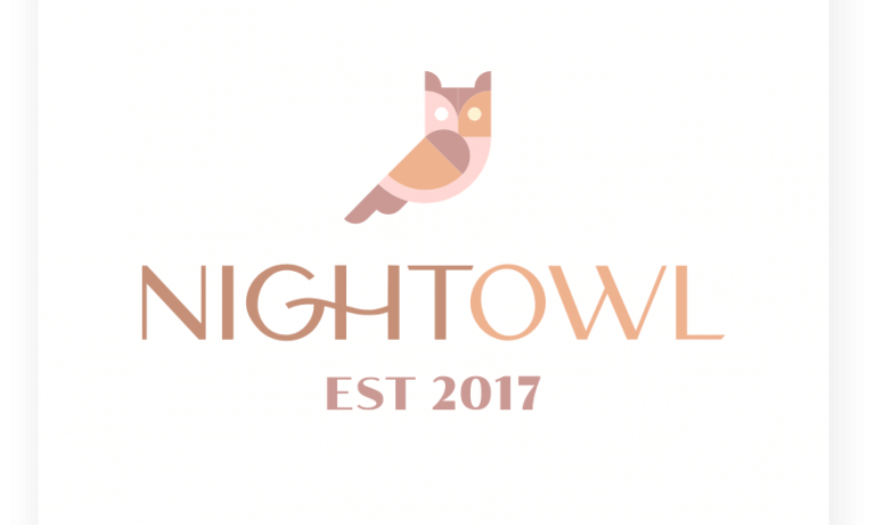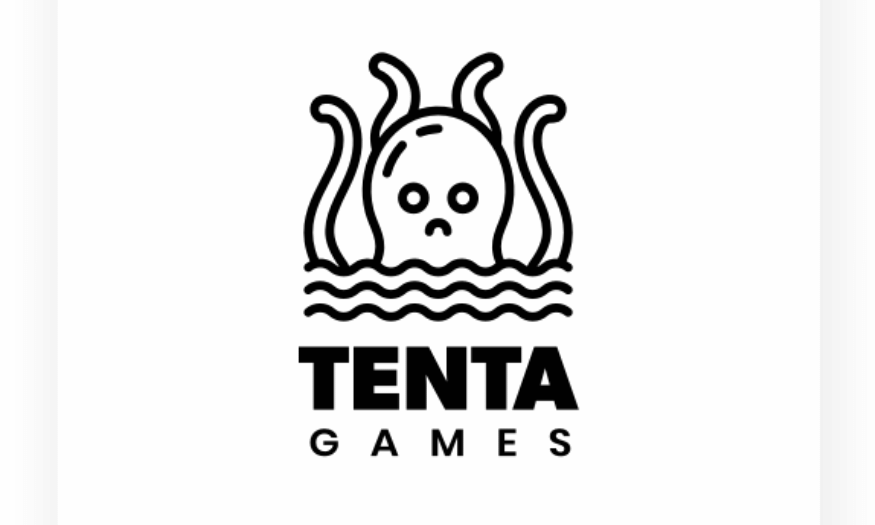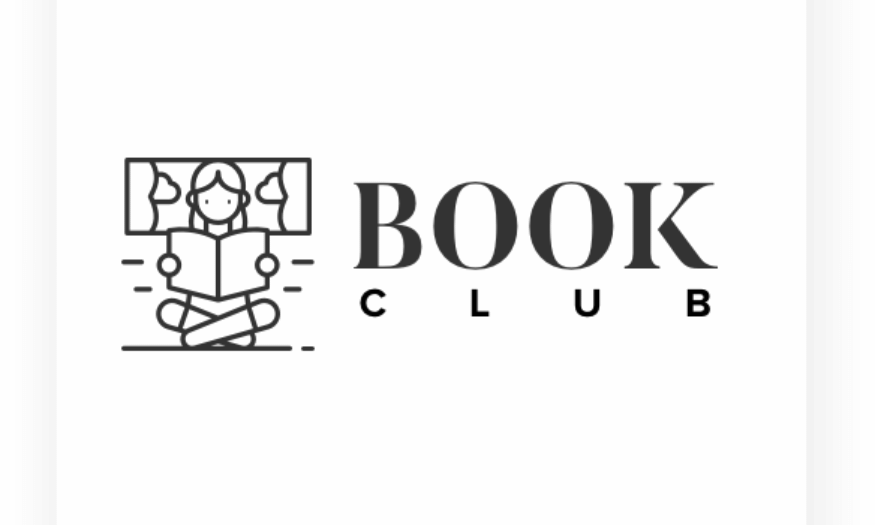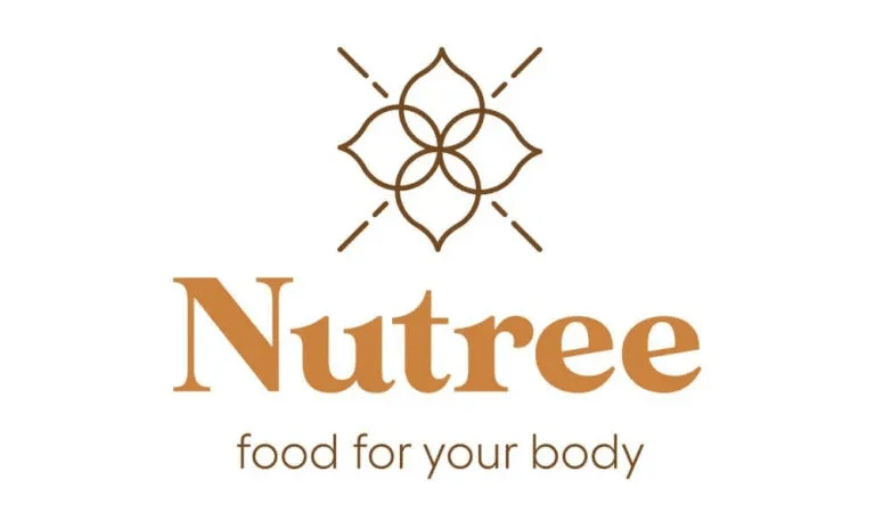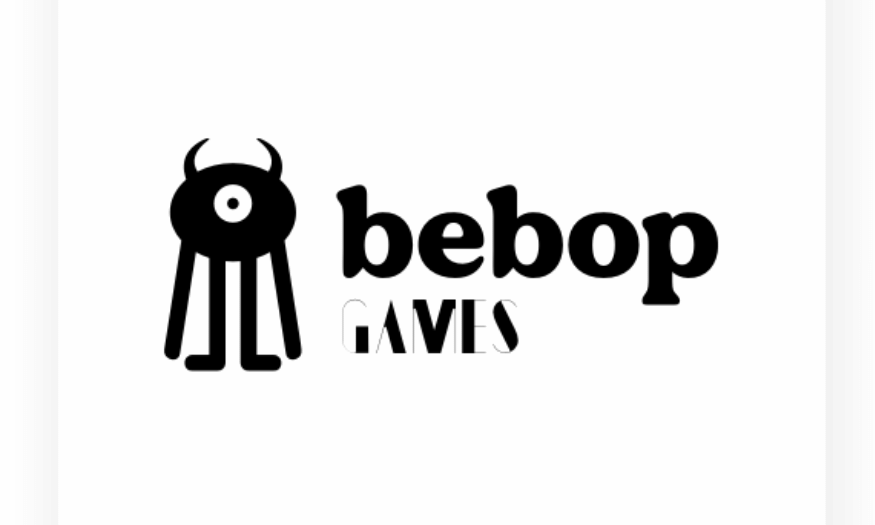
Cách Ghép Font Chữ Thiết Kế Logo Chuyên Nghiệp
Trong thế giới thiết kế logo, việc chọn và ghép font chữ là một trong những yếu tố quan trọng quyết định sự thành công của thương hiệu. Một logo không chỉ cần đẹp mắt mà còn phải truyền tải được thông điệp của doanh nghiệp một cách hiệu quả. Việc kết hợp các font chữ một cách hợp lý không chỉ giúp tạo ra sự độc đáo mà còn làm nổi bật được bản sắc thương hiệu. Trong bài viết này, Sadesign sẽ cùng bạn khám phá các bước cơ bản và những mẹo hữu ích để ghép font chữ một cách chuyên nghiệp, giúp logo của bạn trở nên nổi bật và dễ nhớ hơn.
Cách Ghép Font Chữ Thiết Kế Logo Chuyên Nghiệp
Trong thế giới thiết kế logo, việc chọn và ghép font chữ là một trong những yếu tố quan trọng quyết định sự thành công của thương hiệu. Một logo không chỉ cần đẹp mắt mà còn phải truyền tải được thông điệp của doanh nghiệp một cách hiệu quả. Việc kết hợp các font chữ một cách hợp lý không chỉ giúp tạo ra sự độc đáo mà còn làm nổi bật được bản sắc thương hiệu. Trong bài viết này, Sadesign sẽ cùng bạn khám phá các bước cơ bản và những mẹo hữu ích để ghép font chữ một cách chuyên nghiệp, giúp logo của bạn trở nên nổi bật và dễ nhớ hơn.
1. Ghép hai font chữ từ cùng một họ font
Khi bắt đầu hành trình thiết kế logo, việc lựa chọn font chữ phù hợp là một trong những quyết định quan trọng nhất. Sử dụng font chữ từ cùng một họ không chỉ giúp bạn tạo ra sự hài hòa mà còn mang lại cảm giác nhất quán cho toàn bộ thiết kế. Họ font chữ được phân loại thành nhiều nhóm như serif, sans serif, thảo mộc, và monospace, mỗi nhóm có những đặc điểm riêng, giúp bạn dễ dàng tìm kiếm những font chữ bổ sung cho nhau.
Một lợi thế lớn khi sử dụng font chữ cùng họ là bạn có thể tận dụng đa dạng các kiểu dáng mà chúng cung cấp. Ví dụ, một họ font chữ có thể bao gồm các lựa chọn về trọng lượng (độ dày hoặc độ mỏng), kích thước và cách viết hoa. Điều này cho phép bạn linh hoạt hơn trong việc thiết kế mà vẫn duy trì được sự nhất quán. Logo NIGHTOWL là một ví dụ điển hình, với sự kết hợp hoàn hảo giữa các kiểu chữ trong cùng một họ, tạo nên một cái nhìn gắn kết và dễ nhớ.
Ngoài ra, việc lựa chọn font chữ từ cùng một họ giúp bạn tiết kiệm thời gian tìm kiếm và thử nghiệm. Bạn sẽ không phải lo lắng về việc các font chữ có bị xung đột hay không, vì chúng đã được thiết kế để hòa hợp với nhau. Điều này góp phần tạo ra một trải nghiệm người dùng tốt hơn, khi người xem dễ dàng nhận diện thương hiệu và thông điệp mà bạn muốn truyền tải.
2. Font chữ dày kết hợp tốt với một font chữ mỏng
Một trong những kỹ thuật hiệu quả nhất trong thiết kế logo là tạo ra sự tương phản giữa các font chữ. Sự kết hợp giữa một font chữ dày và một font chữ mỏng không chỉ giúp nâng cao tính thẩm mỹ mà còn làm rõ ràng thông điệp mà bạn muốn truyền tải. Font chữ dày thường mang lại cảm giác mạnh mẽ, trong khi font chữ mỏng lại tạo ra sự tinh tế và nhẹ nhàng.
Khi kết hợp hai loại font chữ này, điểm chính là phải đảm bảo rằng chúng đủ tương phản để người xem có thể dễ dàng phân biệt. Chẳng hạn, trong thiết kế logo cho Bla Bla Bla Podcast, bạn có thể thấy sự kết hợp giữa font chữ dày cho phần "Bla Bla Bla" và font chữ mỏng cho từ "Podcast". Sự phân chia này không chỉ tạo ra một hệ thống phân cấp trực quan mà còn thu hút sự chú ý vào phần tên chính của chương trình.
Hơn nữa, việc sử dụng trọng lượng khác nhau giữa các font chữ cũng giúp tạo ra một thiết kế hài hòa và cân đối. Điều này có thể làm nổi bật các thông điệp quan trọng, đồng thời thể hiện rõ vai trò của từng phần trong tổng thể thiết kế. Sự tương phản này sẽ giúp logo của bạn nổi bật hơn trong mắt người xem và dễ dàng ghi nhớ hơn.
3. Thử Kerning chặt với Kerning rộng
Kerning là yếu tố quan trọng trong thiết kế giúp điều chỉnh khoảng cách giữa các ký tự trong font chữ. Việc thử nghiệm với kerning chặt và kerning rộng có thể tạo ra những hiệu ứng thú vị và giúp tăng cường sự phân biệt giữa các phần trong logo. Một khoảng cách phù hợp giữa các ký tự không chỉ giúp cho văn bản dễ đọc mà còn tạo ra một cảm giác thẩm mỹ nhất định.
Tuy nhiên, khi làm việc với kerning, bạn cần phải tinh tế và cẩn thận. Nếu khoảng cách giữa các ký tự quá gần, nó có thể tạo ra cảm giác chật chội và khó đọc. Ngược lại, nếu khoảng cách quá xa, người đọc có thể cảm thấy bị phân tâm hoặc mất hứng thú. Sự cân bằng giữa hai yếu tố này là rất quan trọng để đảm bảo rằng logo của bạn không chỉ đẹp mà còn dễ nhận diện.
Hãy nhớ rằng, việc điều chỉnh kích thước và kerning cũng có thể giúp bạn tìm ra sự kết hợp hoàn hảo cho logo của mình. Bằng cách thử nghiệm với các cặp font chữ với kerning khác nhau, bạn có thể tạo ra một tổng thể hài hòa và nổi bật. Điều này không chỉ tạo ra một thiết kế ấn tượng mà còn giúp người xem dễ dàng nhận ra và ghi nhớ thương hiệu của bạn.
4. Hai font chữ với hình thái bổ sung
Khi nói đến việc ghép font chữ, hình thái và cảm xúc mà font truyền tải là những yếu tố không thể bỏ qua. Mỗi kiểu chữ mang theo một thông điệp riêng, từ sự chuyên nghiệp cho đến sự vui tươi hay thậm chí là sự ngốc nghếch. Chẳng hạn, font chữ tròn, vui tươi với hình dạng giống như bong bóng sẽ rất phù hợp cho một lời mời sinh nhật trẻ em, trong khi một font chữ nghiêm túc hơn sẽ phù hợp hơn cho một thương hiệu kinh doanh.
Điều quan trọng là bạn cần chọn những font chữ có hình thái bổ sung, tạo nên một tổng thể hài hòa. Logo của Heavy Routine Fitness Center là một ví dụ điển hình về việc kết hợp giữa các font chữ có sự tương đồng trong hình thái nhưng vẫn nổi bật từng phần riêng biệt. Sự bổ sung này không chỉ tạo ra một thiết kế đẹp mắt mà còn giúp người xem dễ dàng hiểu được thông điệp mà thương hiệu muốn truyền tải.
Việc chọn font chữ với hình thái bổ sung cũng giúp tạo ra một cảm giác nhất quán trong thiết kế. Khi người xem thấy hai font chữ bổ sung cho nhau, họ sẽ dễ dàng nhận diện thương hiệu và cảm thấy thoải mái hơn khi tiếp xúc với nó. Hãy thử nghiệm với những font chữ có hình thái tương phản nhưng vẫn giữ được sự liên kết trong cảm xúc để tạo ra một logo độc đáo và ấn tượng.
5. Sử dụng Serif và Sans Serif cùng nhau
Việc kết hợp giữa font chữ Serif và Sans Serif là một trong những phương pháp phổ biến và hiệu quả nhất trong thiết kế logo. Font chữ Serif, như Times New Roman, có những nét hoa trang trí ở cuối các ký tự, tạo ra cảm giác trang trọng và cổ điển. Ngược lại, font chữ Sans Serif, như Arial, lại mang đến sự đơn giản và hiện đại, không có những chi tiết trang trí phức tạp.
Sự kết hợp này không chỉ mang lại sự cân bằng trong thiết kế mà còn tạo ra độ tương phản rõ rệt giữa các phần khác nhau của logo. Khi sử dụng font chữ Serif cho phần tiêu đề và font chữ Sans Serif cho phần phụ, bạn có thể dễ dàng thu hút sự chú ý vào thông điệp chính mà không làm mất đi sự rõ ràng. Logo của Book Club là một ví dụ điển hình, khi chữ serif mang đến sự tinh tế cho từ "cuốn sách", trong khi chữ sans serif tạo cảm giác dễ tiếp cận và hấp dẫn.
Tuy nhiên, khi kết hợp hai loại font này, bạn cần lưu ý về trọng lượng và kiểu dáng tổng thể của chúng. Cả hai font chữ nên có sự khác biệt rõ rệt để tránh cảm giác nhàm chán hoặc thiếu sự sáng tạo. Với sự chú ý đến chi tiết và sự cân nhắc trong việc lựa chọn, bạn có thể tạo ra một thiết kế logo đầy ấn tượng và dễ nhớ.
6. Hãy thử heading truyền thống với body trang trí
Trong thiết kế logo, việc xác định vai trò của từng font chữ trong hệ thống phân cấp là vô cùng quan trọng. Tiêu đề thường là phần thu hút sự chú ý nhất, vì vậy chúng cần có kích thước lớn và trọng lượng nặng hơn để tạo ấn tượng mạnh mẽ. Hơn nữa, tiêu đề cũng thiết lập giai điệu cho thương hiệu, khiến nó trở thành điều đầu tiên mà người xem tiếp xúc.
Trong trường hợp của Mystic Theory Beauty, việc sử dụng font chữ truyền thống cho phần tiêu đề không chỉ thể hiện sự hiện đại mà còn tạo cảm giác đáng tin cậy cho thương hiệu. Bằng cách kết hợp với một font chữ trang trí cho phần body, logo mang lại một sự tương phản hấp dẫn và hiệu ứng trực quan mạnh mẽ. Khán giả sẽ cảm nhận được sự chuyên nghiệp nhưng vẫn đầy nghệ thuật, thu hút họ đến với thương hiệu.
Việc ghép nối giữa một font chữ truyền thống cho tiêu đề và một font chữ trang trí cho phần body giúp tạo ra một hệ thống phân cấp rõ ràng. Điều này không chỉ làm nổi bật những thông điệp chính mà còn tạo ra một thiết kế dễ dàng ghi nhớ. Khi bạn xem xét cách mà mỗi phần tương tác với nhau, bạn sẽ nhận thấy sự ảnh hưởng mạnh mẽ mà sự kết hợp này mang lại cho tổng thể logo.
7. Sử dụng heading trang trí với body truyền thống
Trong thiết kế logo, việc lựa chọn font chữ không chỉ đơn thuần là quyết định về hình thức mà còn là cách truyền tải cảm xúc. Nếu bạn muốn logo của mình gợi lên sự vui vẻ và thoải mái, việc kết hợp một heading trang trí với một body chữ truyền thống là một lựa chọn hoàn hảo. Font chữ trang trí thường có sự sáng tạo và độc đáo, trong khi font chữ truyền thống mang lại cảm giác chuyên nghiệp và đáng tin cậy.
Một điều thú vị là sự thay đổi trong cách sử dụng font chữ giữa phần tiêu đề và nội dung có thể tạo ra độ tương phản mạnh mẽ, giúp logo nổi bật hơn. Việc sử dụng heading trang trí để thu hút ánh nhìn của người xem, kết hợp với body truyền thống sẽ tạo cảm giác thoải mái nhưng vẫn tạo ấn tượng chuyên nghiệp. Logo Fitness của TailorBrands là một ví dụ điển hình cho cách kết hợp này, nơi mà sự vui vẻ và tính chuyên nghiệp hòa quyện với nhau.
Tuy nhiên, nếu bạn không tìm thấy sự phù hợp giữa các kiểu chữ mà mình đã chọn, đừng lo lắng. Thực tế, có rất nhiều cách để thử nghiệm và tìm ra sự kết hợp hoàn hảo cho logo của bạn. Hãy mở rộng tầm nhìn và sáng tạo với những kiểu chữ khác nhau, để tạo ra một thiết kế thật sự ấn tượng và độc đáo.
8. Không sử dụng font chữ quá giống nhau
Khi ghép font chữ, nguyên tắc vàng mà bạn cần ghi nhớ chính là: Tương phản, tương phản, và một lần nữa là tương phản! Đây là yếu tố cốt lõi giúp bạn tạo ra một thiết kế logo hiệu quả. Sự kết hợp giữa các font chữ serif và sans serif là một minh chứng cho điều này, khi chúng tạo ra độ tương phản vừa đủ để làm nổi bật các phần khác nhau của logo.
Khi chọn cặp font chữ, hãy cân nhắc đến nhiều yếu tố như kích thước, trọng lượng, màu sắc, khoảng cách và phong cách. Những yếu tố này sẽ giúp bạn đánh giá xem liệu hai font chữ có thực sự bổ sung cho nhau hay không. Nếu bạn cảm thấy không thể xác định được phần nào là quan trọng trong logo, có thể bạn đã chọn những font chữ quá giống nhau về kiểu dáng, trọng lượng và kích thước.
Một thiết kế logo sẽ trở nên kém hiệu quả nếu các font chữ không thể phân biệt được với nhau. Người xem sẽ gặp khó khăn trong việc nhận ra thông điệp mà bạn muốn truyền tải, và điều này có thể dẫn đến sự nhầm lẫn. Hãy chắc chắn rằng mỗi font chữ đều có vai trò riêng và đóng góp vào tổng thể của logo một cách rõ ràng và dễ hiểu.
9. Tránh ghép các font chữ quá khác nhau
Mặc dù việc tạo ra sự tương phản là rất quan trọng, nhưng quá nhiều sự khác biệt giữa các font chữ có thể khiến thông điệp của bạn trở nên khó hiểu. Các font chữ cần phải có sự tương đồng nhất định, giống như việc các hành tinh trong cùng một hệ mặt trời. Nếu bạn kết hợp những font chữ quá khác nhau, người xem sẽ dễ dàng cảm thấy bối rối và không nắm bắt được ý nghĩa mà bạn muốn truyền tải.
Để xác định sự phù hợp giữa các font chữ, bạn có thể nhìn bằng mắt thường hoặc áp dụng một số quy tắc cơ bản. Một nguyên tắc đơn giản là kiểm tra tỷ lệ và chiều cao x (chiều cao của ký tự "x" trong mỗi font chữ). Nếu chiều cao x tương tự nhưng hình dáng và phong cách khác nhau, đây có thể là sự kết hợp tốt.
Ngoài ra, hãy thử chọn hai font chữ có nét chữ mảnh nhưng khác nhau về kích thước, hoặc chọn một font chữ có trọng lượng khác biệt nhưng kiểu dáng tương tự. Những sự lựa chọn này sẽ giúp tạo ra một thiết kế logo không chỉ độc đáo mà còn dễ dàng nhận diện và ghi nhớ.
10. Ba là đủ
Trong thiết kế logo, quy tắc giới hạn số lượng font chữ thường được khuyến nghị là ba. Nguyên nhân chính là bởi vì khi bạn sử dụng nhiều hơn ba font chữ, thiết kế có thể trở nên mất cân đối và dễ gây nhầm lẫn cho người xem. Một số nhà thiết kế có thể cho rằng việc phá vỡ quy tắc này là cần thiết để sáng tạo, nhưng trong trường hợp này, việc giữ nguyên quy tắc sẽ mang lại kết quả tốt hơn.
Nếu bạn cảm thấy cần thêm một font chữ thứ tư, hãy thử điều chỉnh những font đã có. Bạn có thể làm cho chúng trở nên đậm hơn, in nghiêng hoặc gạch chân để tạo ra sự khác biệt mà không cần phải thêm một kiểu chữ mới. Việc này không chỉ giúp thiết kế trông gọn gàng hơn mà còn giữ cho nó không quá phức tạp, giúp người xem dễ dàng tiếp nhận thông điệp.
Trước khi quyết định sử dụng một font chữ mới, hãy tự hỏi bản thân lý do đằng sau sự lựa chọn đó. Mỗi font chữ bạn chọn nên có lý do cụ thể và mang lại lợi ích cho tổng thể thiết kế của logo. Nếu bạn không thể thuyết phục chính mình về sự cần thiết của font chữ đó, thì rất có thể khán giả cũng sẽ cảm thấy như vậy.
11. Hãy chắc chắn rằng chúng dễ đọc
Một trong những mục tiêu chính của việc sử dụng font chữ trong thiết kế logo là nâng tầm hình ảnh và tạo ra sự kết nối cảm xúc với khán giả. Tuy nhiên, nếu người xem không thể đọc được văn bản, tất cả nỗ lực của bạn sẽ trở nên vô nghĩa. Do đó, việc đảm bảo rằng các font chữ bạn chọn dễ đọc là điều vô cùng quan trọng.
Font chữ cần phải rõ ràng và dễ nhận diện, không chỉ trên màn hình mà còn trong bản in. Điều này đặc biệt quan trọng trong bối cảnh ngày nay, khi ngày càng nhiều người truy cập thông tin qua các thiết bị di động. Một logo đẹp nhưng khó đọc sẽ khiến người dùng nhanh chóng bỏ qua, và điều này có thể ảnh hưởng đến ấn tượng đầu tiên của họ về thương hiệu.
Hãy xem xét kích thước, độ dày và kiểu dáng của font chữ bạn sử dụng. Đảm bảo rằng chúng không chỉ phù hợp với phong cách thiết kế mà còn dễ dàng cho người xem tiếp nhận. Một logo hiệu quả không chỉ đẹp mà còn phải dễ dàng truyền tải thông điệp mà bạn muốn gửi gắm. Hãy chú ý đến yếu tố này để tạo ra những thiết kế ấn tượng và dễ ghi nhớ.
12. Kết luận
Tóm lại, ghép font chữ trong thiết kế logo không chỉ đơn thuần là lựa chọn một vài kiểu chữ mà còn là nghệ thuật kết hợp và tạo dựng bản sắc thương hiệu. Bằng cách nắm vững các nguyên tắc cơ bản và áp dụng những mẹo hữu ích, bạn có thể tạo ra những logo ấn tượng, phản ánh đúng giá trị và tầm nhìn của doanh nghiệp. Liên hệ ngay Sadesign để nâng cấp phần mềm thiết kế tạo nên font chữ hoàn hảo nhé.